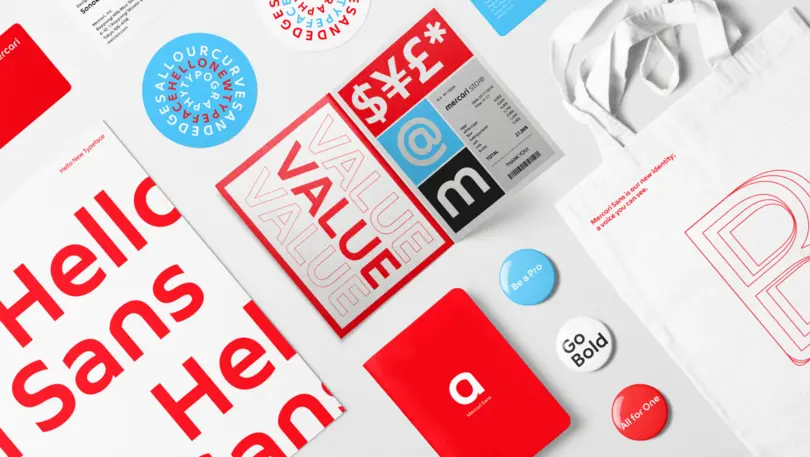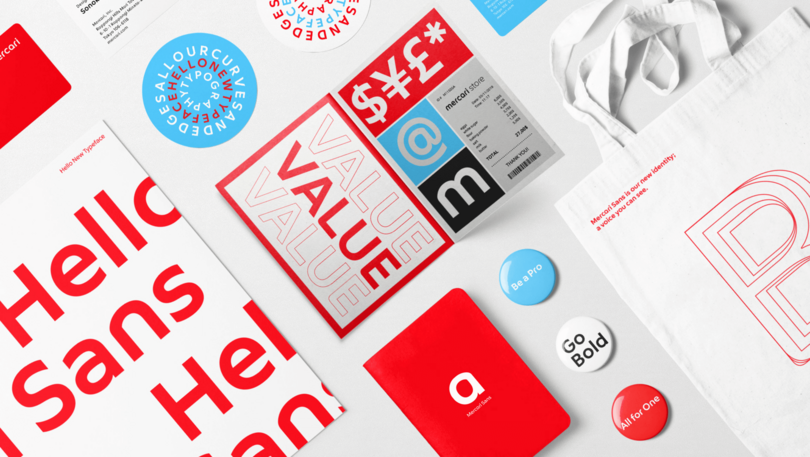
事例のご紹介:Mercari Sans
「メルカリらしさ」を文字に。ブランドの“声”をつくるコーポレートフォント「Mercari Sans」
Monotype は、 2019年10⽉、フリマアプリ「メルカリ」のサービスを運営する株式会社メルカリのコーポレートフォントMercari Sansを制作しました。
Mercari Sansの開発の背景にあったのは、オンライン、オフラインを問わず、あらゆる接点で一貫した「メルカリらしさ」を届けたいという想いでした。2019年のロゴタイプ変更を機に、ブランドの“目に見える声”として文字の重要性に着目。新しいロゴタイプや和文書体「たづがね角ゴシック」と調和しながら、Webサイト、印刷媒体、IR資料、広告、サービスロゴなど幅広い場面で活用できる欧文コーポレートフォントの開発が始まりました。デザインでは、「トラスト(安心、信頼)」と「オープン(公平さ、親しみやすさ)」というブランドの価値を、どのように文字の表情として伝えるかが大切なテーマとなりました。
制作には、メルカリの社内デザインチーム、ロゴタイプを手がけたTakram、Monotypeが参加。オンラインでデザイン案を共有しながら、小文字の形や切り口の角度など細部まで検討を重ねました。議論のなかでは、求めていた文字の形が現れた瞬間、チーム全体から思わず「これだ!」という声が上がったことも。フォントという具体的な形を一緒につくることで、「自分たちのブランドらしさとは何か」をチームで見つめ直し、共通認識を深めていくプロセスにもなりました。
さらにMercari Sansには、入力する文脈に応じて小文字「a」の字形が自動で切り替わるなど、ブランドと実用性を両立する工夫も盛り込まれています。Thin、Regular、Bold、Extra Boldの4ウェイトが制作され、文字の切り口やフトコロの形まで細かな調整が行われました。